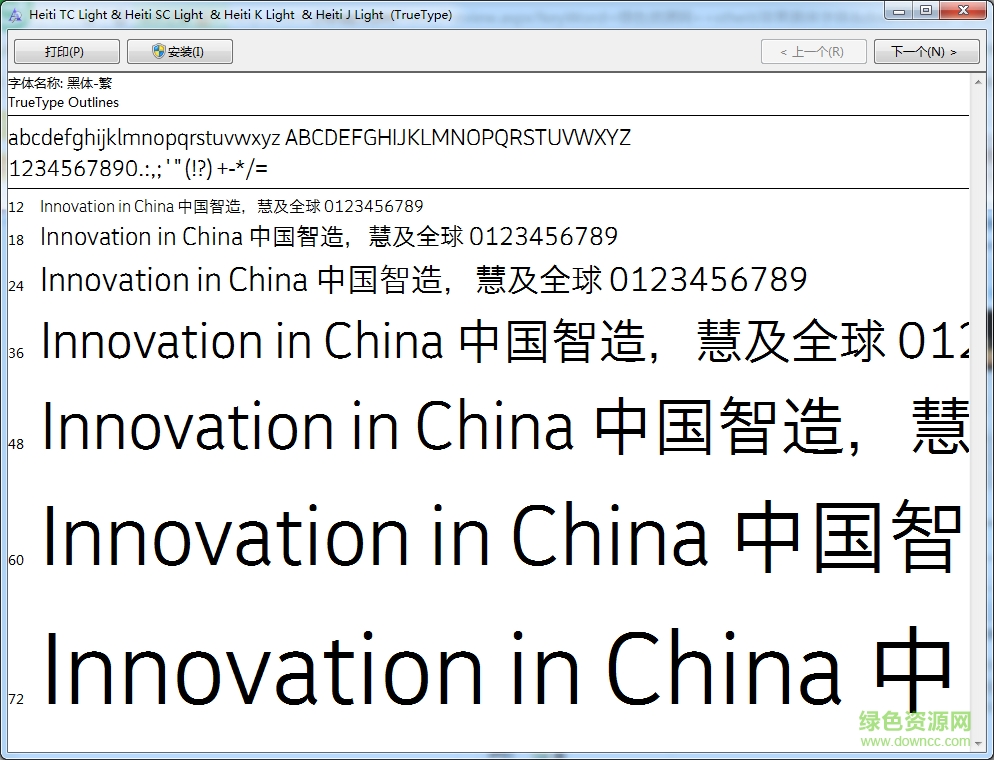
stheiti-light.ttc字體可在windows代替蘋果黑體字體使用,大方得體,實(shí)用性很強(qiáng),綠色資源網(wǎng)還提供了包括幾何體、過渡體、舊式風(fēng)格無襯線字體等不同風(fēng)格的英文字體供大家下載!
黑體字體由來
清末萌芽57年簡化字體后定形。筆劃橫平豎直,粗細(xì)一致,筆劃較粗,方頭方尾形成方黑一體而得名,又稱方體。
圓黑體特點(diǎn)
由黑體演變而來,方角變圓角,方頭變圓頭,點(diǎn)、撇、捺、挑、勾略帶弧,并稍加長。筆畫的方粗和粗圓,雖然字形一樣,所取得的效果確各異。粗方是厚重平板之感;粗圓呈厚重而靈活的格調(diào)。因此,印刷術(shù)上出現(xiàn)圓黑體,具有較強(qiáng)的沖擊力,給人圓潤活動(dòng)之效果,又有時(shí)代感。